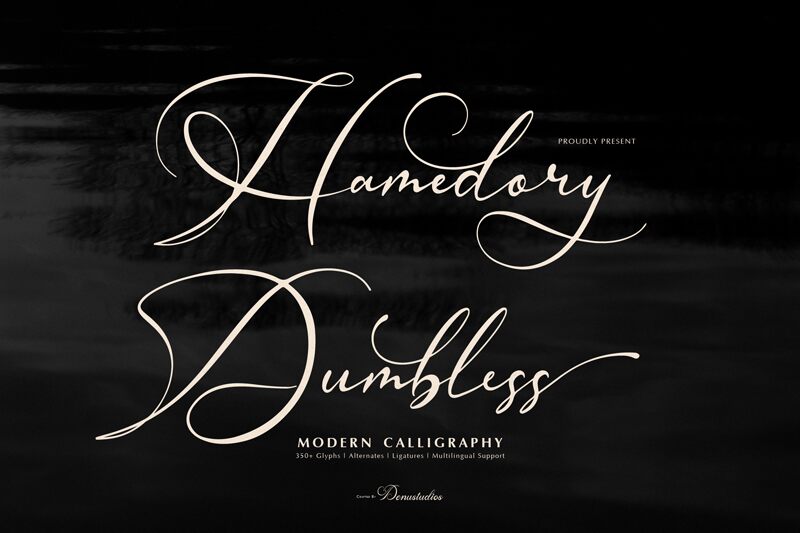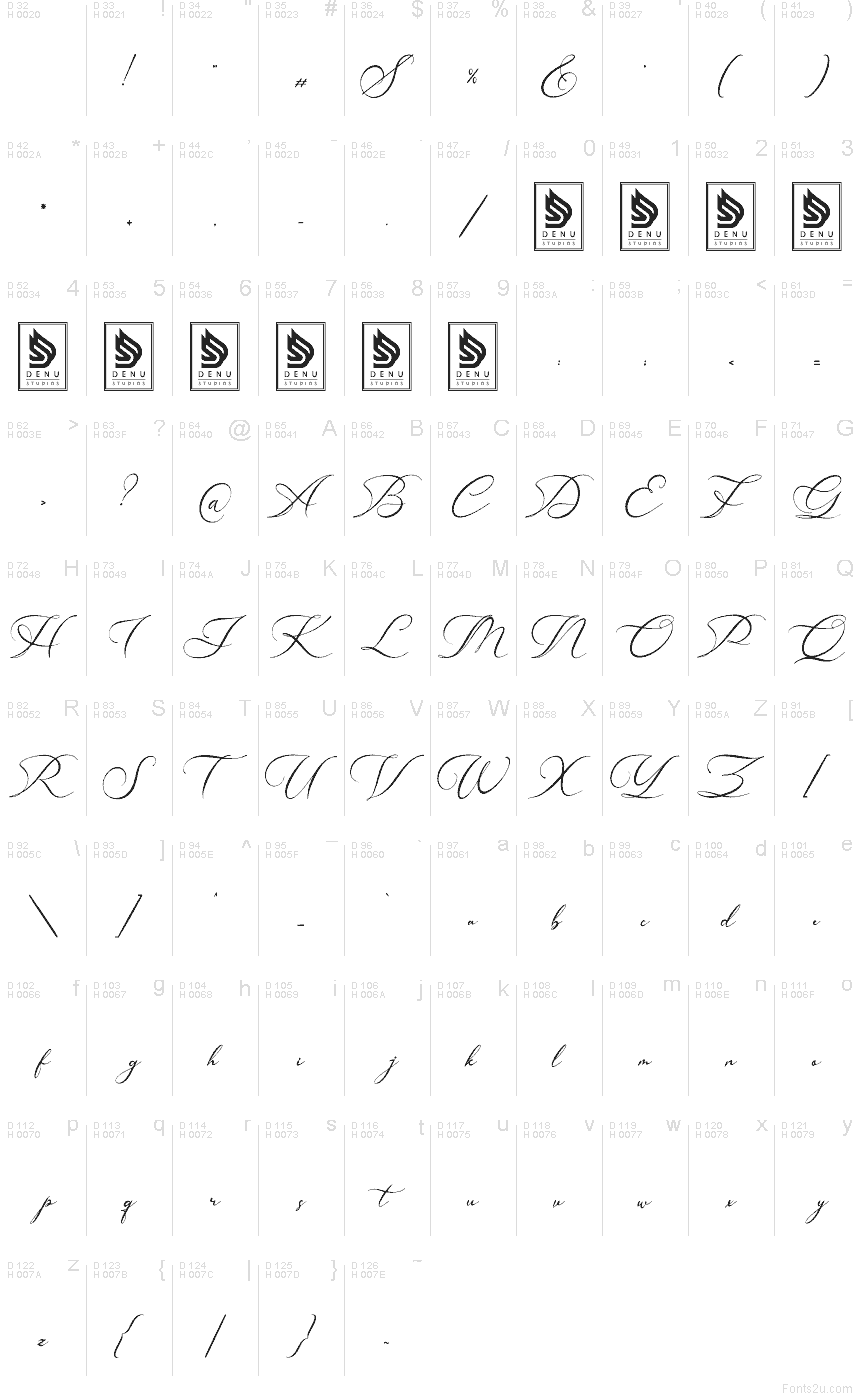
Hamedory Dumbless de Denustudios es una fuente caligráfica gratuita de estilo Copperplate, definida por sus trazos de entrada dinámicos y sus largas florituras etéreas que aportan a las letras un aire formal y romántico. El contraste entre las líneas finas y los trazos principales, más marcados, le otorga una elegancia equilibrada, ideal para nombres, firmas y frases cortas donde el movimiento caligráfico debe destacar.
Esta fuente gratuita es perfecta para papelería de bodas, branding de belleza o perfumería, packaging exclusivo, portadas de revistas y tarjetas de presentación que necesiten un toque manuscrito refinado. También funciona de maravilla en monogramas y encabezados de redes sociales, ya que sus extensiones decorativas permiten que incluso un texto breve luzca solemne y especial.